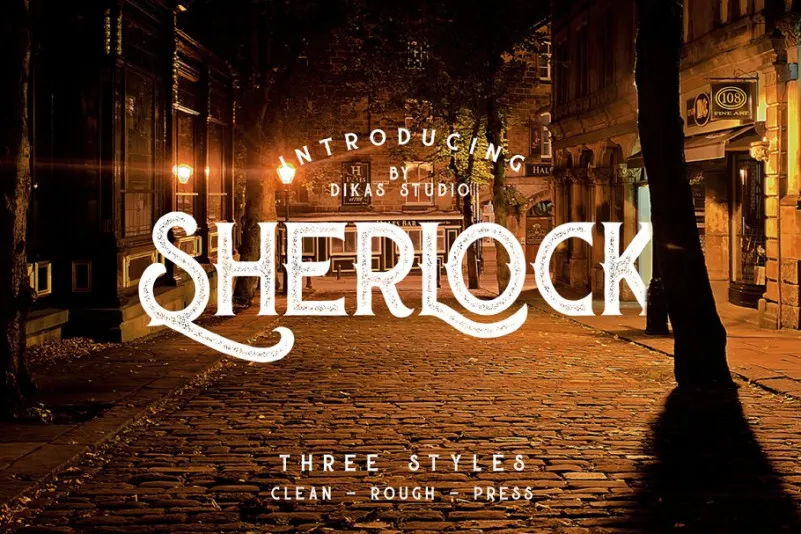
Sherlock Typeface – Download Grátis
Estou aqui uma sugestão de descrição para a página de download da fonte Sherlock Typeface: Descubra a arte cuidadosamente detalhada do Sherlock Font! Esse estilo gothic foi criado por handcraft, inspirado nos clássicos posters antigos. Ideal para qualquer trabalho de marca que busca um toque vintage e sofisticado. O Sherlock oferece três estilos: Clean, Rough & Press, cada um com personalidade única e traços delicadamente desenhados. Ele também inclui recursos OpenType, o que o torna particularmente útil para criações vintage. Este font perfeito combina perfeitamente em design de marca, logotipos, embalagens, convites, citações, camisetas e cartazes. Descubra como ele pode revolucionar seu estilo gráfico!